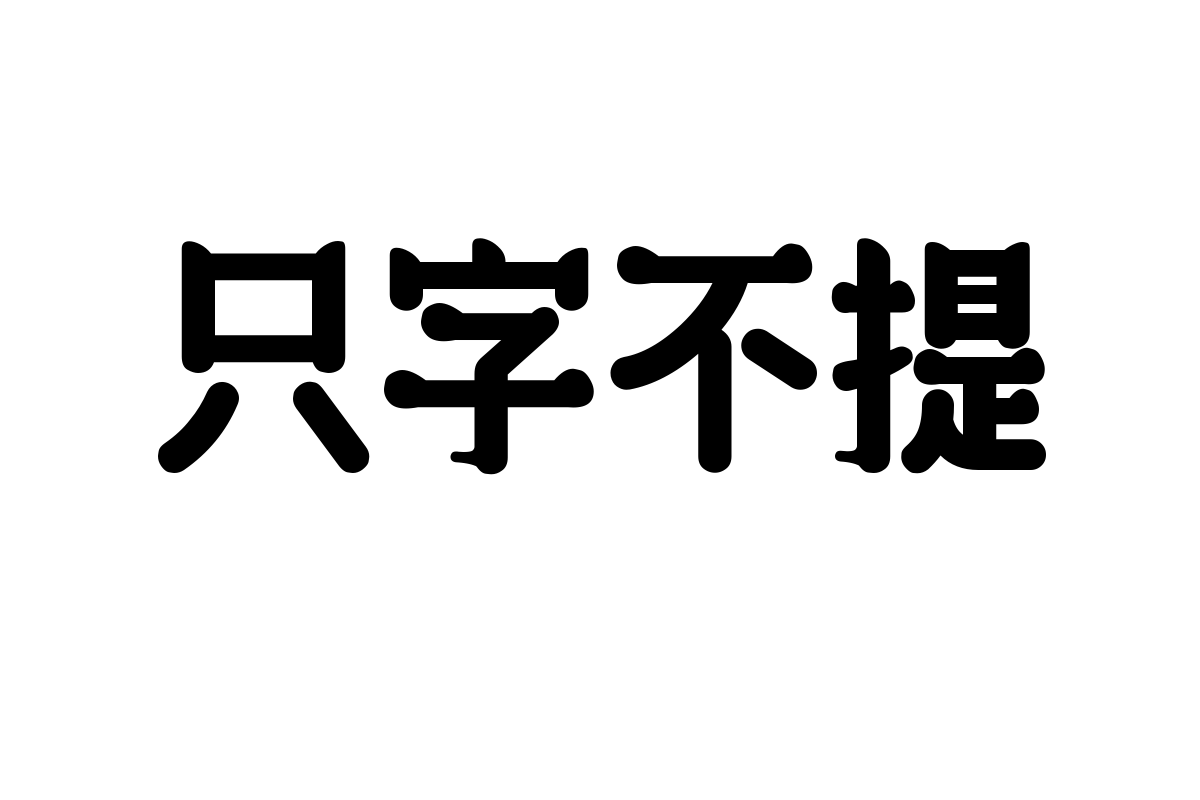
朴月体是一种现代中文字体,由造字工房公司开发。它以其优雅、简洁的设计风格和良好的可读性而受到广泛欢迎。朴月体采用无衬线设计,字形清晰,易于阅读。它的线条流畅,没有过多的装饰,给人一种简约而现代的感觉。
朴月体的字体大小范围很广,从小到大都可以很好地适应不同的需求。无论是用于标题、正文还是广告,朴月体都能提供良好的视觉效果。此外,朴月体还具有很好的适应性,可以在不同的设备上显示得很好,包括桌面计算机、笔记本电脑、平板电脑等。
总的来说,朴月体是一款非常实用的中文字体,适合用于各种需要清晰、易读的文本展示场合。